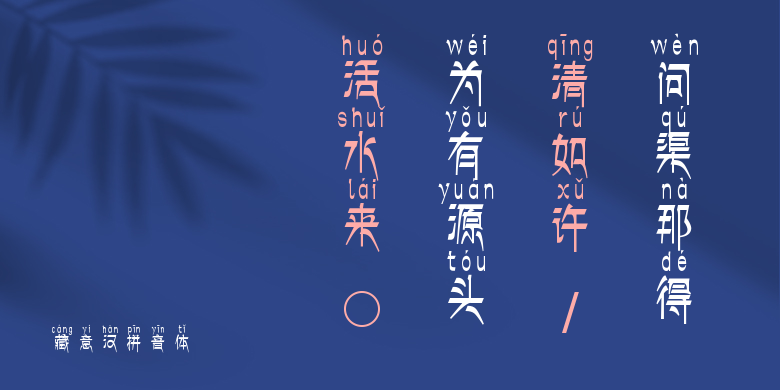
藏意汉拼音体
藏意汉拼音体,这款字体结构工整、笔画清晰,兼顾美观与易读性,适用于标题、正文、海报、包装、LOGO 等多种场景。字形优雅稳定,风格百搭耐看,适配日常排版与创意设计,让文字呈现更舒适、更具质感。藏意汉拼音体一笔一画,皆是细节,以均衡的比例、流畅的线条打造舒适视觉体验,字形端正大气,风格简约现代。无论是商业设计、品牌宣传还是日常排版,都能轻松驾驭,让文字更有格调与力量。藏意汉拼音体字体下载。